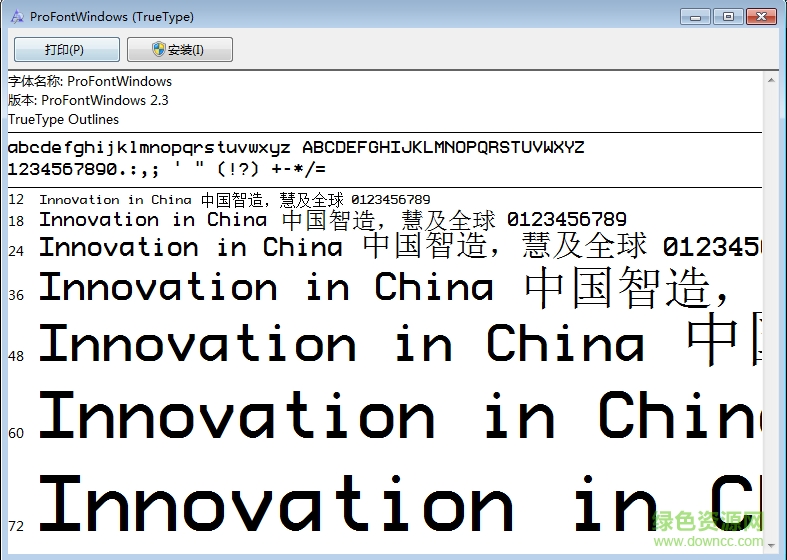
profont是windows上識(shí)別度極高的網(wǎng)頁(yè)字體,編程人士們最?lèi)?ài),其小字號(hào)端正簡(jiǎn)潔,有著很好的視覺(jué)體驗(yàn),綠色資源網(wǎng)誠(chéng)意推薦!
與Monaco類(lèi)似的位圖字體,你能夠在Mac、Windows和Linux上面使用。小字號(hào)的時(shí)候表現(xiàn)好。非Mac平臺(tái)上Monaco的最佳替代。喜歡小字號(hào)且不怕眼睛疲勞的同學(xué)可以考慮。
ProFont 是受到一小撮碼農(nóng)推崇的終端位圖字體,這字體很古老,好處就是9pt的小字也非常清晰犀利,可識(shí)別性極強(qiáng)。